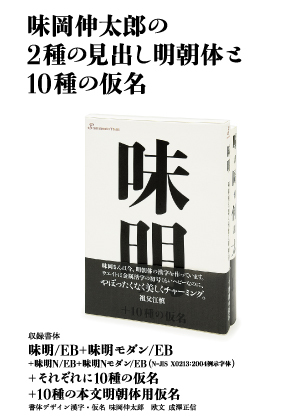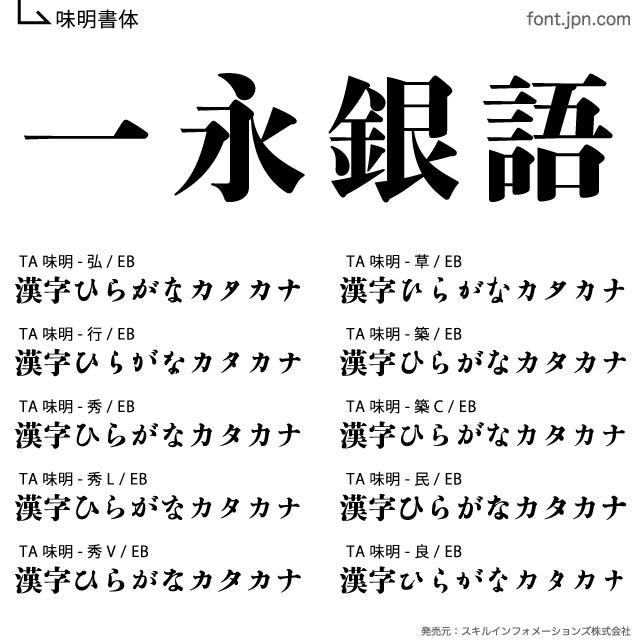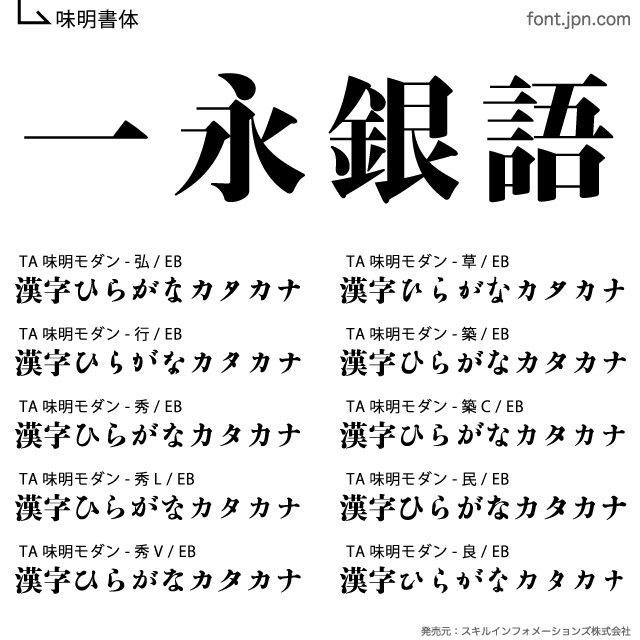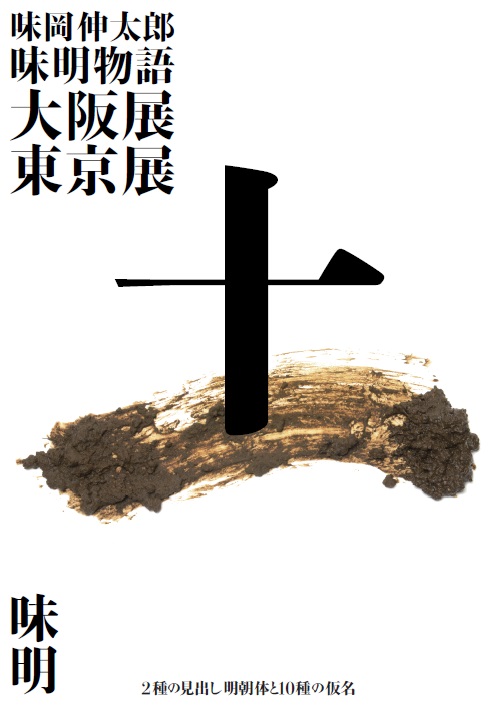
味明
スキルインフォメーションズから、かなのタイプフェイス「小町・良寛」を制作したグラフィックデザイナー・味岡伸太郎氏デザインによる見出し明朝体フォント「味明」の販売が2月1日より開始された。
「味明」は味岡伸太郎氏が漢字と仮名、アーティストの成澤正信氏が欧文のデザインを担当。漢字部分は味明モダンの2書体あり、ひらがな・カタカナは10書体、それぞれを組合せると合計50書体となる。動作環境は、Windoes10/8/7(32bit、64bit対応)、MacOSX10.3以降。 データ形式は、オープンタイプフォントで価格は50,000円(税別)となっている。
味岡氏は書体デザインについて「味明は、線画とのコントラストが強調されるように、横画は可能な限り細く、先端の打ち込みをやや太くするだけで、それも目立たないようにほとんど直線で、水平に処理し、全ての太さを同一にした。 味明モダンは味明のエレメントを更にシャープにさせ、欧文書体にオールドローマンとモダンローマンがあるような、2種類の明朝体をデザイン。両書体ともに柔らかさや優しさを失わず、品よく仕上がったと自負している。」と延べている。
見出し明朝体「味明」および、他のいくつかのタイプフェイスのカタログ。